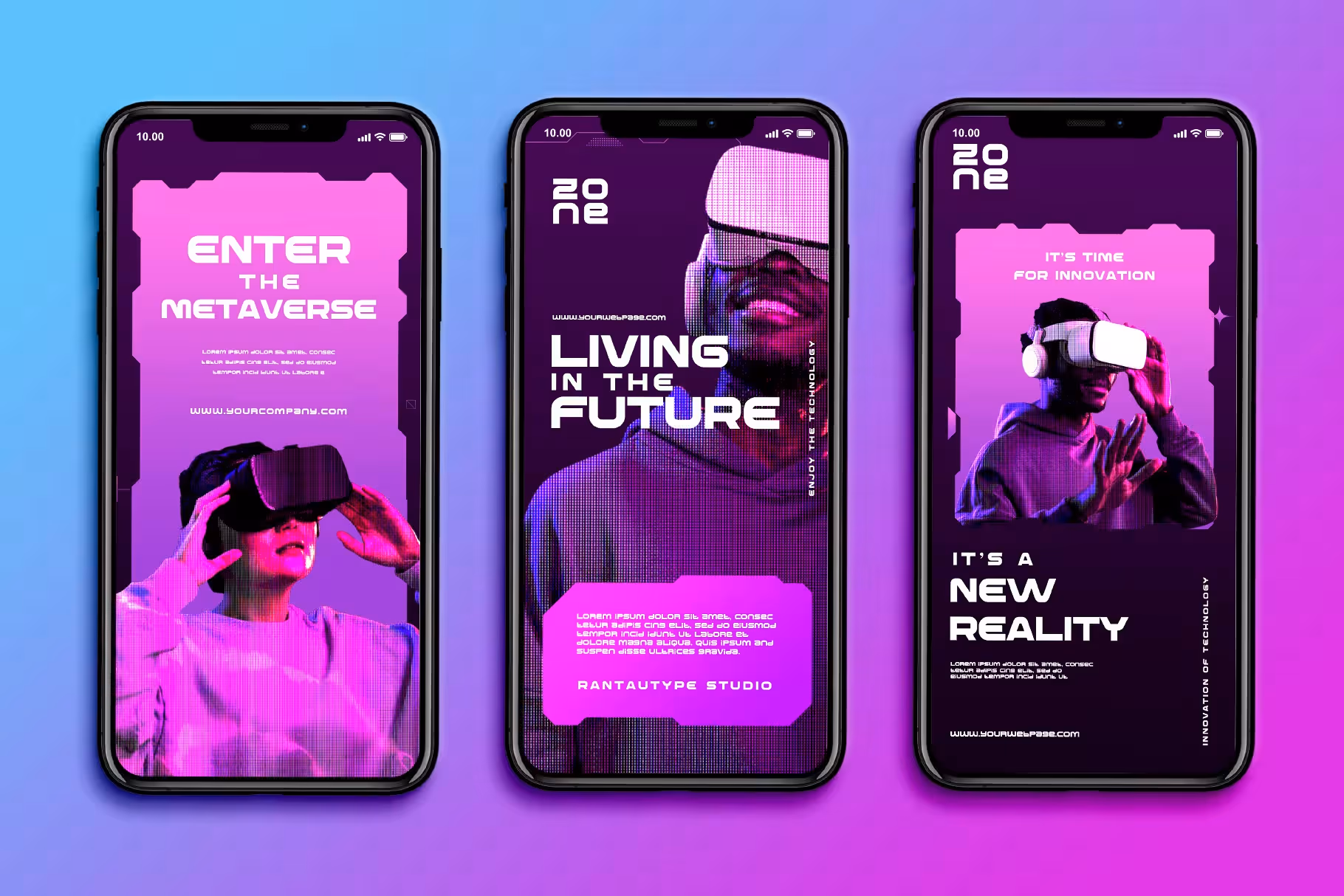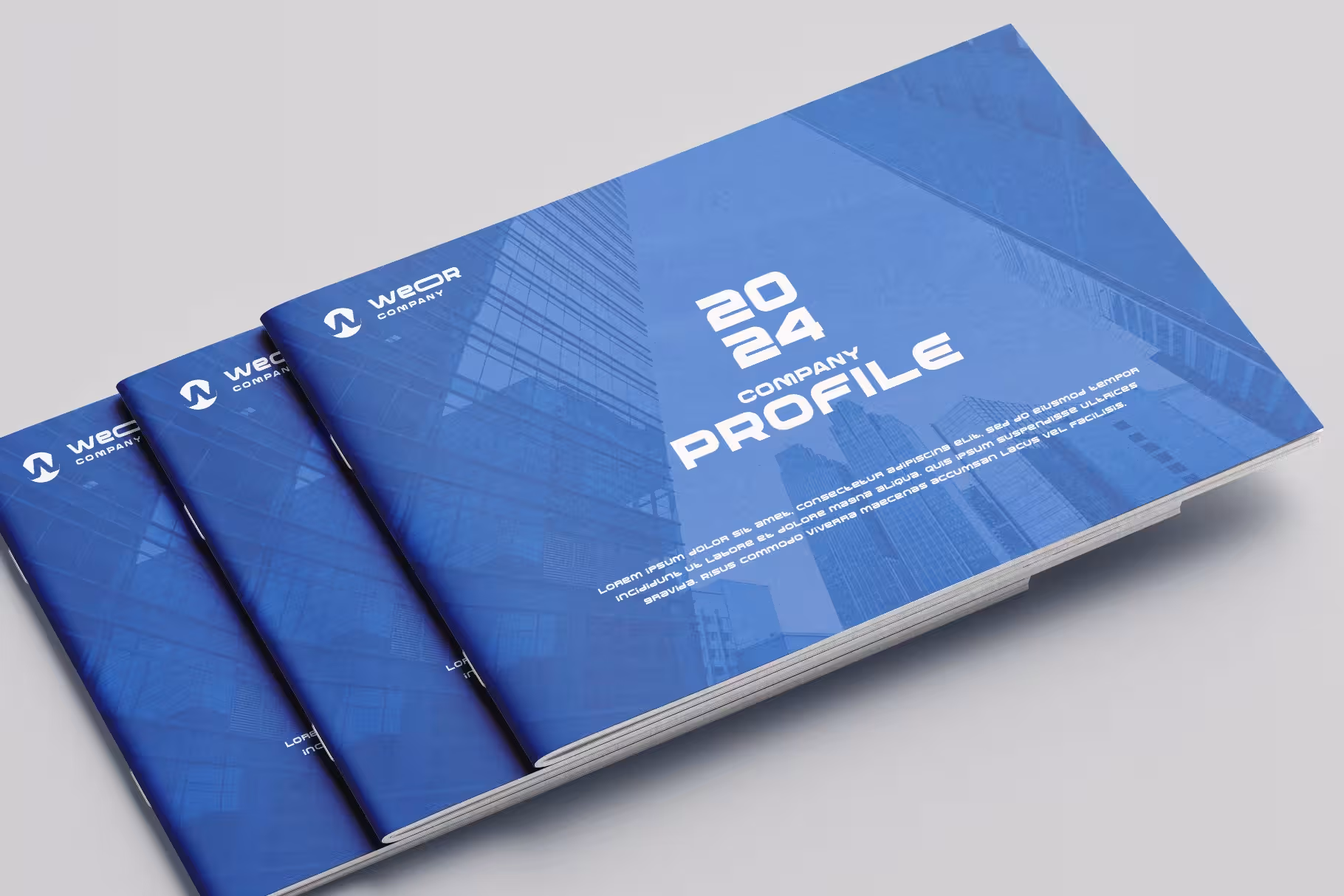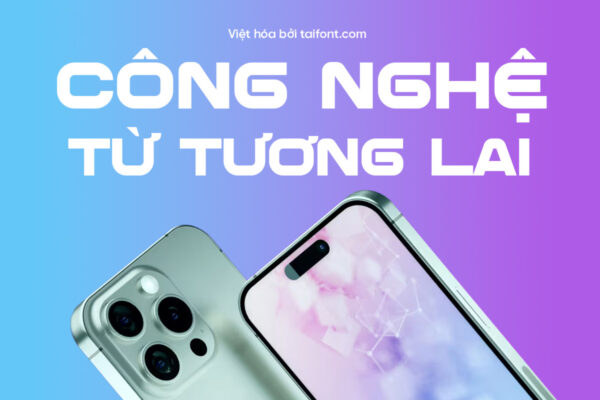
Giới thiệu về Font TF Magios Việt hóa
TF Magios Việt hóa là một font chữ không chân (sans-serif) nổi bật với thiết kế hiện đại, sắc nét và đầy tính công nghệ. Font này toát lên vẻ tinh tế, gọn gàng và có chút tương lai, lý tưởng để tạo điểm nhấn chuyên nghiệp và thu hút mọi ánh nhìn trong các thiết kế đòi hỏi sự tiên tiến và phong cách tối giản.
Với đặc điểm là nét không chân hiện đại, tính thẩm mỹ cao và phong thái sắc sảo, Magios là lựa chọn lý tưởng cho các thiết kế muốn truyền tải sự hiện đại, mạnh mẽ và sự độc đáo, đặc biệt là trong các lĩnh vực:
- Thiết kế hiện đại và công nghệ cao: Hoàn hảo cho các thương hiệu trong ngành công nghệ, phần mềm, thiết bị điện tử, hoặc các dịch vụ kỹ thuật số. Font này giúp truyền tải sự tiên phong, đổi mới và sự tinh xảo trong từng sản phẩm, dịch vụ.
- Thiết kế Trí tuệ Nhân tạo (AI): Lý tưởng cho các ứng dụng, website, tài liệu hoặc sự kiện liên quan đến AI, machine learning, và các công nghệ tương lai. Magios giúp tạo ra một không khí chuyên nghiệp, thông minh và đáng tin cậy.
- Branding (Nhận diện thương hiệu): Phù hợp cho logo, tagline hoặc bộ nhận diện thương hiệu của các công ty, doanh nghiệp muốn truyền tải sự hiện đại, tinh tế và uy tín. Magios giúp xây dựng một hình ảnh thương hiệu vững chắc và dễ nhận diện.
- Thiết kế tạp chí và ấn phẩm chuyên ngành: Thích hợp cho các tiêu đề chính, lời dẫn hoặc nội dung bài viết trong các tạp chí khoa học, công nghệ, hoặc các ấn phẩm chuyên môn khác.
Với TF Magios Việt hóa, bạn có thể dễ dàng thổi hồn hiện đại, sự tinh tế và vẻ đẹp tương lai vào các thiết kế, tạo ra những sản phẩm không chỉ đẹp mắt mà còn cực kỳ ấn tượng và có khả năng thu hút sự chú ý tối đa.